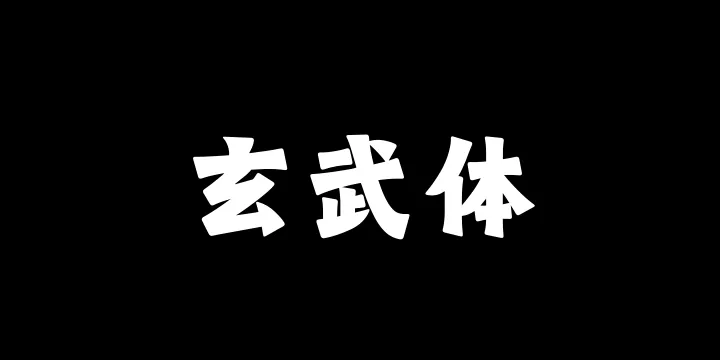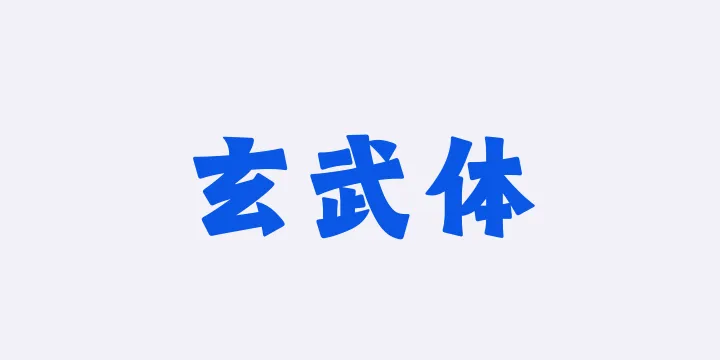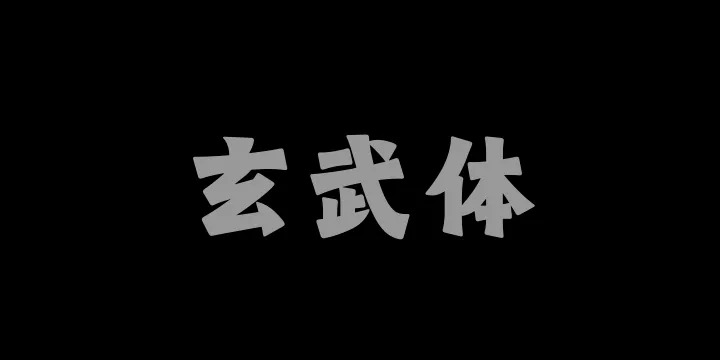
字体全名: 山海玄武体
字体简介: 山海玄武体,包含简体汉字6763个,。字体以楷体为骨架,同时将魏碑之魂注入字体造型之中。结体紧密,行笔有力,错落有致,险中求稳。多用方笔,险劲而富于变化,行笔轻重交错,刚劲果断。这款字体气势磅礴,彰显楷书和魏碑的气韵,同时兼顾排版的实用性,适合应用于传统节庆场合、书籍封面、影视娱乐等多样的使用场景。